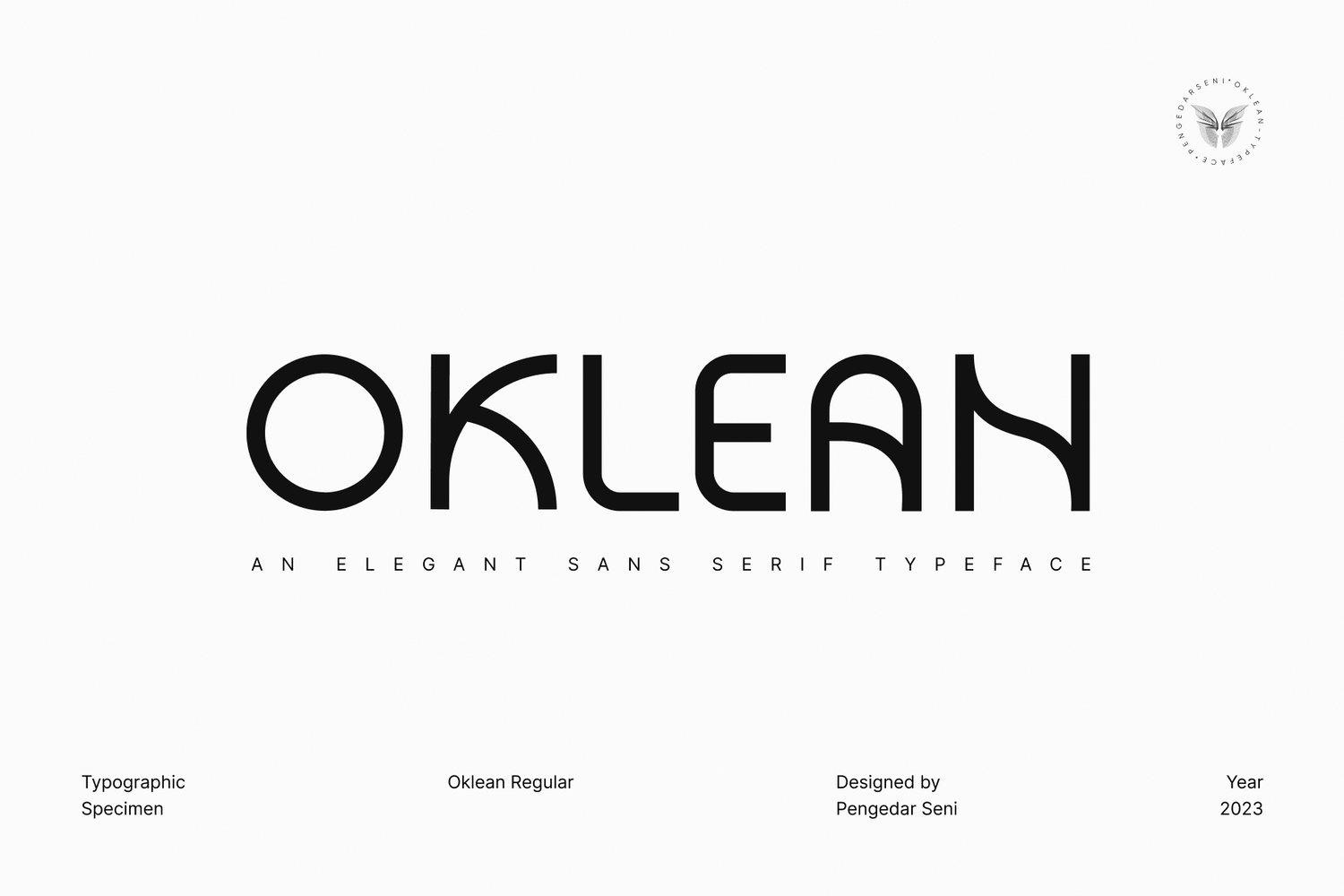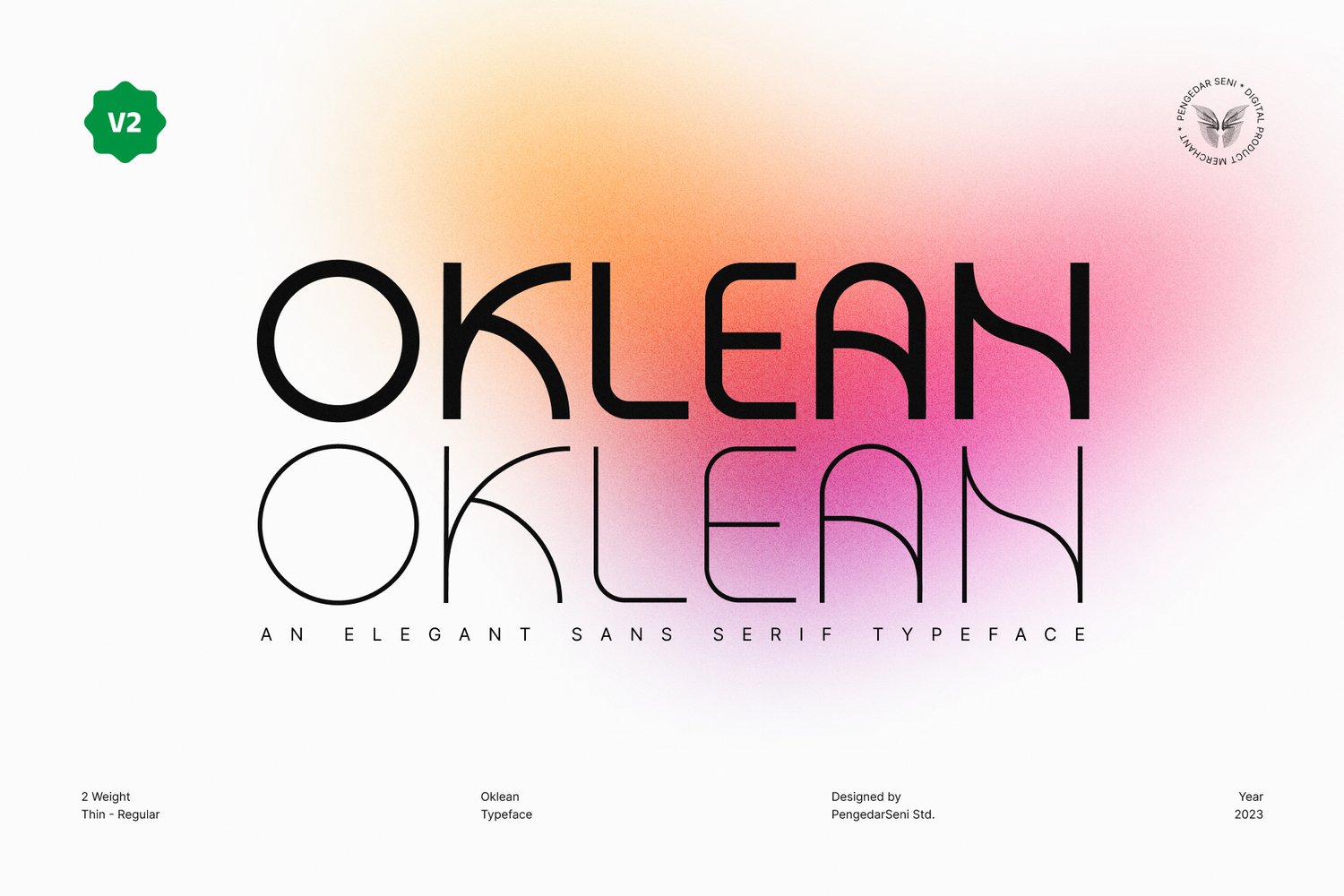
Mencari font yang pas buat logo dan branding itu gampang-gampang susah. Kadang terlalu ramai, kadang terlalu kaku. Nah, kalau kamu lagi cari font sans serif yang clean, modern, dan tetap punya karakter kuat, artikel ini buat kamu.
Kenapa Font Itu Penting Banget Buat Branding?
Font bukan sekadar huruf. Dia bisa mewakili kepribadian brand, menunjukkan apakah kamu profesional, playful, premium, atau minimalis. Salah pilih font, bisa bikin brand kamu kehilangan kesan pertama yang kuat.
Tips Memilih Font untuk Logo:
- Perhatikan Kesederhanaan
- Logo yang bagus biasanya simple. Font yang terlalu dekoratif sering kali susah dibaca.
- Pastikan Mudah Dibaca di Berbagai Ukuran
- Harus tetap jelas walau ukurannya kecil, misal di favicon atau watermark.
- Sesuai dengan Identitas Brand
- Apakah brand kamu lebih ke arah modern, tradisional, fun, atau elegan?
- Cocok untuk Kombinasi Desain
- Font logo sebaiknya bisa dikombinasikan dengan font lain (sebagai body text), misalnya pairing dengan Inter.
👀 Kenalin: Oklean Typeface – Solusi Logo Clean, Modern, dan Elegan
Oklean V1
Dirancang khusus untuk logo, Oklean V1 punya bentuk karakter yang unik, seimbang, dan terlihat bersih.
Setiap huruf dirancang dengan konsep:
Bright / Clean / Clear / Cool / Nature / Minimal / Smart / Urban / Balanced.
Cocok banget buat branding startup, produk kreatif, desain fashion, hingga agensi.
Oklean V2
Versi terbaru dari Oklean hadir dengan dua berat font: Regular dan Thin. Oklean V2 memberikan fleksibilitas lebih dalam eksplorasi branding, terutama buat kamu yang suka tampilan tipis, ringan, dan modern.
Ditambah dengan:
- Perbaikan bentuk huruf dan karakter khusus
- Dukungan multi-bahasa (Latin & Cyrillic)
- Tampil keren untuk UI/UX, packaging, hingga editorial branding
✨ Kenapa Harus Coba Oklean?
✅ Desain minimalis dan modern
✅ Tersedia dua versi (Regular & Thin)
✅ Font sans serif geometris yang cocok untuk berbagai jenis branding
✅ Support banyak bahasa dan karakter unik
✅ Bisa dipadukan dengan font Inter untuk tampilan profesional
📌 Siapa yang Cocok Pakai Oklean?
- Desainer grafis yang butuh font branding kuat
- UMKM & startup yang ingin tampil stand out
- Agensi branding untuk kebutuhan identitas visual klien
- UI/UX designer yang butuh font bersih dan tipis
- Pemilik produk digital yang ingin tampil elegan dan profesional
🎨 Penutup
Font adalah investasi kecil yang bisa berdampak besar. Oklean memberikan keseimbangan antara kesederhanaan dan karakter, menjadikannya pilihan tepat untuk logo dan branding masa kini.